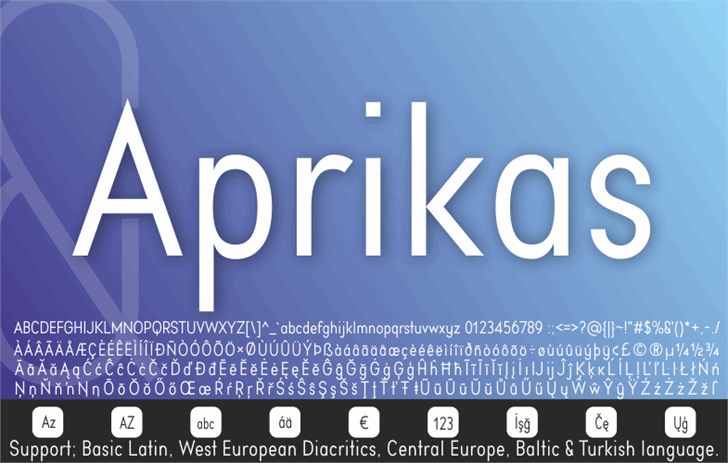
Aprikas Font Family – Fonte Grátis
Aprikas Font Family
A fonte Aprikas Font Family é uma escolha perfeita para designers que procuram elegância e modernidade em suas criações digitais. Este famoso conjunto de fãs, criado pelo StudioTypo, oferece um estilo moderno e minimalista com sua tipografia sans-serif limpa e eficiente. Para quem está planejando projetos comerciais, o StudioTypo disponibiliza uma versão limitada para demonstração, mas não hesite em explorar mais profundamente suas opções de fãs. A Aprikas Font Family traz uma paleta vibrante de letras que se destacam por sua simplicidade e eficácia, tornando-a perfeita para aplicativos digitais variados. Sujeitos a mudanças tecnológicas avançadas, continuamos a criar fontes que proporcionam um design elegante e moderno para uma variedade de ambientes. Para designers atentos à qualidade gráfica, o StudioTypo apresenta uma fonte de grande valor. Eles não hesitaram em fornecer opções completas e incrivelmente detalhadas, garantindo que a Aprikas Font Family seja um investimento valioso para projetos profissionais. Assim, os designers podem aproveitar os benefícios da Aprikas Font Family com certeza, independentemente de onde estejam em seu processo criativo.
Designer: Studiotypo